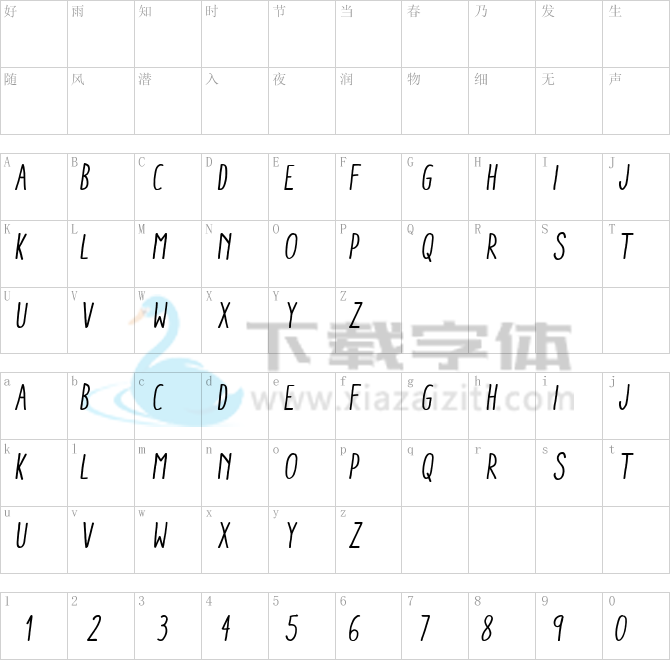
Aracne Condensed Regular Italic.ttf字体下载,这款字体结构工整、笔画清晰,兼顾美观与易读性,适用于标题、正文、海报、包装、LOGO 等多种场景。字形优雅稳定,风格百搭耐看,适配日常排版与创意设计,让文字呈现更舒适、更具质感。Aracne Condensed Regular Italic.ttf字体下载一笔一画,皆是细节,以均衡的比例、流畅的线条打造舒适视觉体验,字形端正大气,风格简约现代。无论是商业设计、品牌宣传还是日常排版,都能轻松驾驭,让文字更有格调与力量。Aracne Condensed Regular Italic.ttf字体下载字体下载。